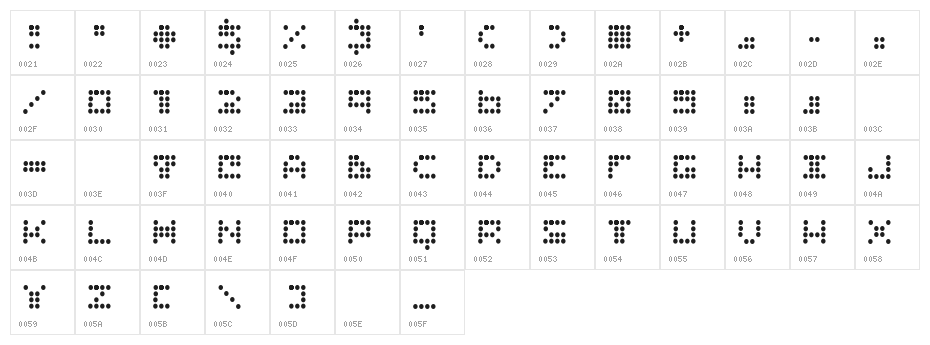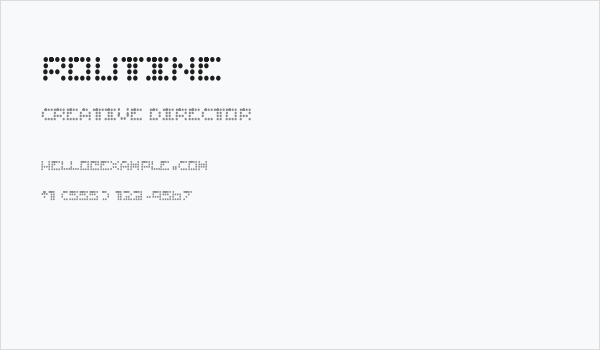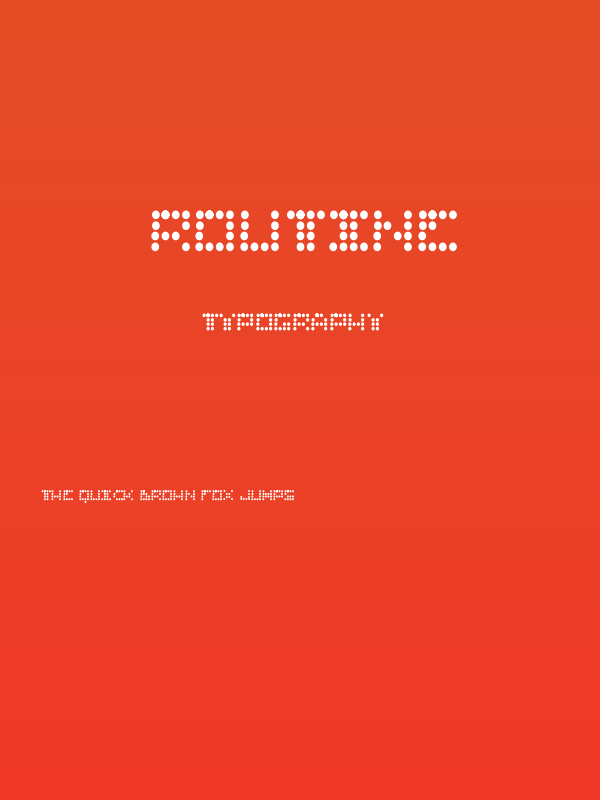
Routine Font
✎ Dotted
| Anwendungsfall | Headlines, Logos, Digital displays |
| Vorgeschlagene Projekte | Ideal for digital displays, tech-themed designs, creative posters, and modern branding. |